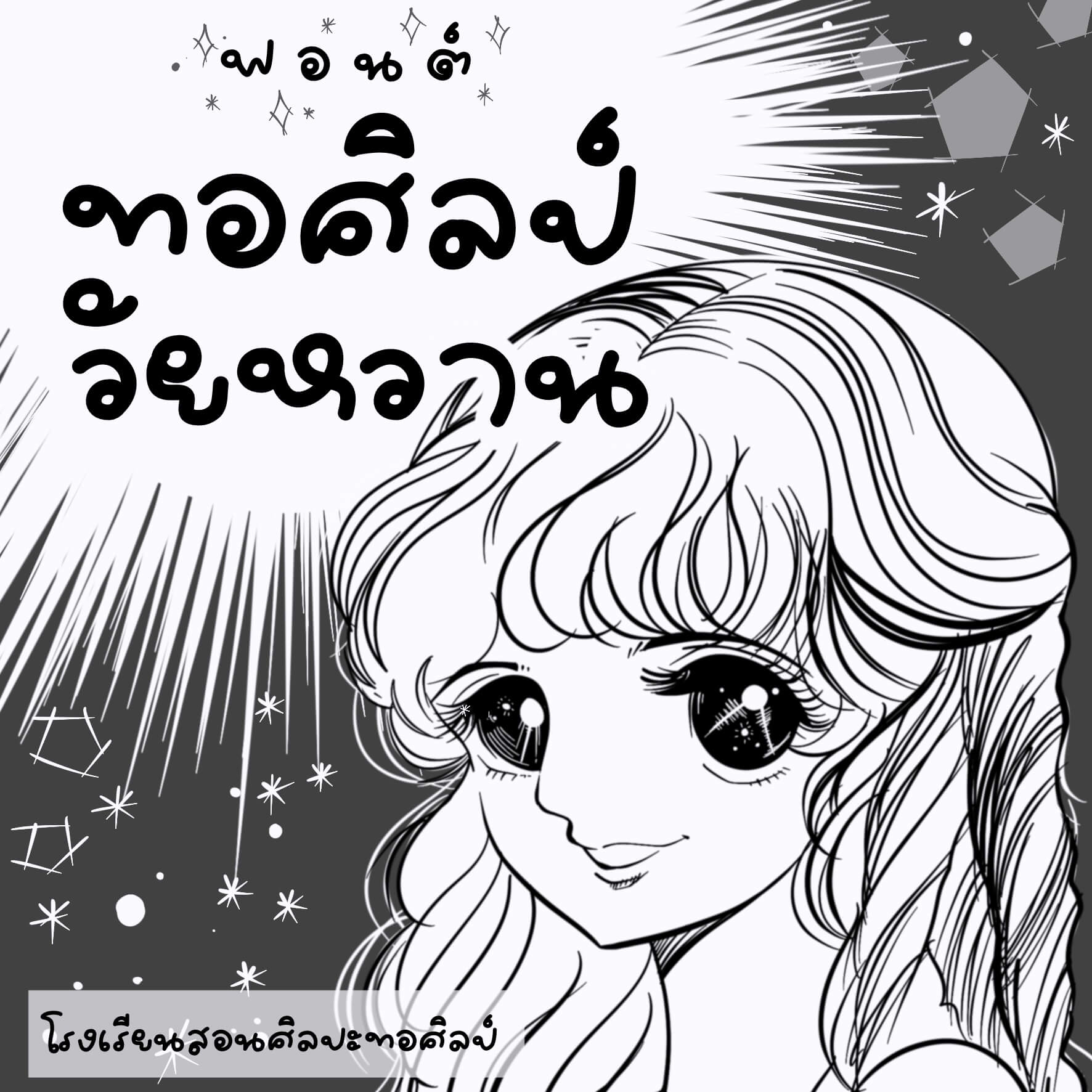
ทอศิลป์ วัยหวาน (Torsilp WaiWan)
สมัยเรียนศิลปะ ยุคนั้นสมัยโน้น ลายมือแบบนี้นิยมมาก คุ้นตาจากนิตยสารวัยรุ่นประเภทวัยหวาน ใยไหม เป็นหนังสือกลอนเปล่า เฝ้าฝัน ละเมอหา ผมเองพยายามคัดฝึกลายมือแบบนี้อยู่เหมือนกัน กะว่าเอาไว้เขียนเฟรนด์ชิปสวยๆ